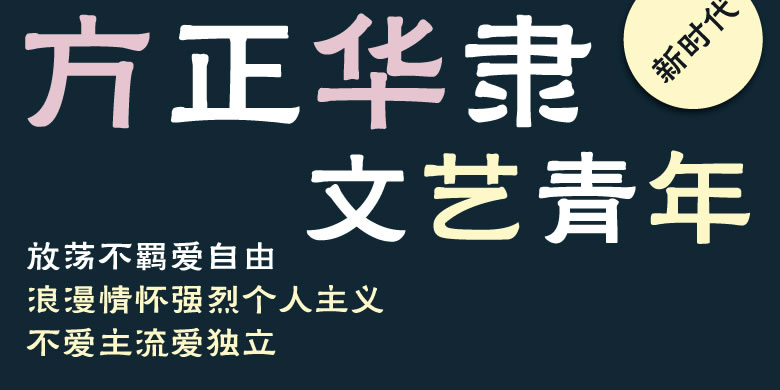
品牌:方正字库设计师:陆华平发行时间:2003字库编码:大陆简体(GB2312-80)、大陆繁体(GB12345-90)、简繁扩展(GBK)、港台地区(BIG-5)分类:隶书
方正华隶的风格接近隶书时代后期石刻,以较为平直的笔法来表现隶书的“蚕头雁尾”,整体风格朴茂端方,古朴优美,隶书韵味浓郁。这款字的笔画粗细较为一致,平直短促,中宫宽松,外轮廓扁方统一。方正华隶适用于传统古典类的标题和短文。